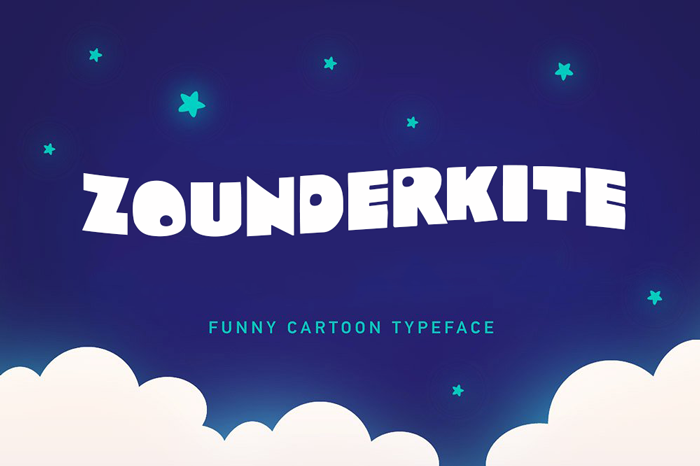
Introduzimos a famosa família de fonts Zounderkite do Designer Hamilton. Este conjunto de fontes foi criado especificamente para estilos visuais divertidos e engraçados, ideal para elementos gráficos de logomarca animada ou títulos curtos. O designer Iconian Fonts compartilhou este recurso criativo projetado especialmente para livros infantis e cartões de agradecimento, ajudando a celebrar e trazer o encanto da criança em cada projeto. Zounderkite é uma excelente escolha para qualquer aplicação que exige um toque engraçado e divertido, seja ele em logomarcas animadas ou nos títulos dos mais fofos livros infantis.